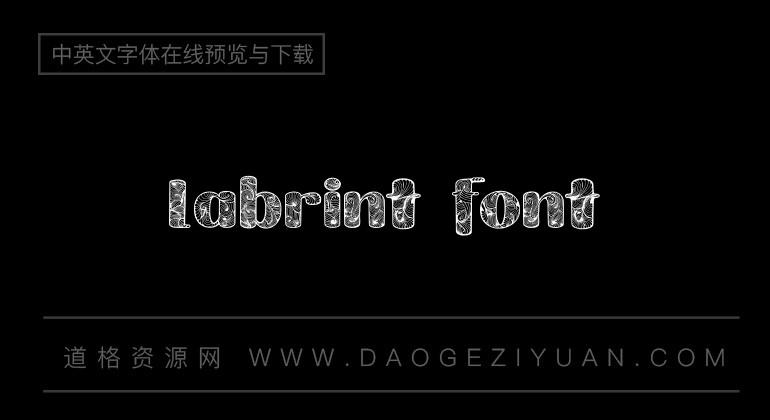
Labrint Font
Labrint是一款现代风格的字体,由设计师Milos Mitrovic于2020年发布。该字体的特点是线条流畅,字母间距紧凑,具有现代、科技感,适用于数字设计、标志、包装和海报设计等领域。Labrint共有三种字重,包括常规、粗体和斜体,可供用户根据需要自由选择。
Labrint Font是一款非常不错的手写艺术字体,具有很好的视觉感,适合于文化类的宣传设计、商业类品牌的广告和产品包装设计以及个性化文字排版等较多场景。